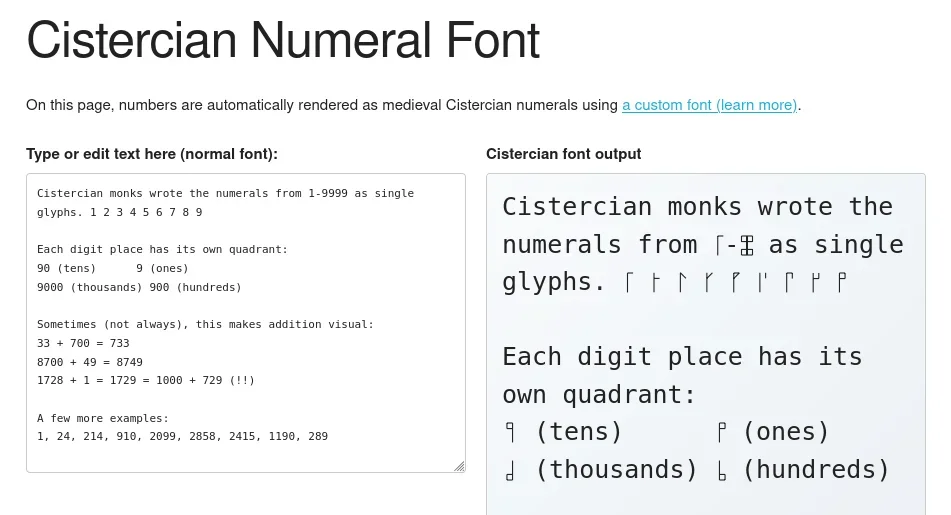
중세 시대 숫자, 커스텀 폰트로 부활!
커스텀 폰트(Custom Font)를 활용하여 중세 시대의 시스테르 시토 숫자 표기법을 구현하여 시각적 표현을 극대화함
덧셈 연산(Addition) 시 시각적 피드백을 제공하는 독특한 특징을 보이며, 필기 방식의 장점을 강조함
글리프(Glyph) 디자인의 혁신성과 유니코드(Unicode) 코드 포인트 할당에 대한 논의가 이루어짐
시스테르 시토 숫자 표기법의 시각적 특징
본 기술은 커스텀 폰트(Custom Font)를 활용하여 시스테르 시토 숫자 표기법을 구현, 덧셈 연산 시 시각적 피드백을 제공한다. 특히, 7-세그먼트 폰트(7-segment font)와 유사하게 숫자를 표현하여 직관성을 높였다. 이러한 시각적 표현은 수학적 개념(Mathematical Concept)을 시각화하는 데 기여하며, 사용자 경험을 향상시킨다.
필기 방식과 인쇄 방식의 차이점
커뮤니티에서는 필기 방식의 혁신성을 강조하며, 인쇄 방식의 한계를 지적한다. 필기(Handwriting)는 개별적인 글리프(Glyph) 생성이 자유롭고, 즉각적인 공유가 가능하다. 반면, 인쇄는 사전 정의된 글리프(Predefined Glyph)를 사용해야 하므로, 새로운 글리프 추가에 제약이 따른다. 이러한 차이는 글꼴 디자인(Font Design)의 혁신을 저해하는 요인으로 작용한다.
유니코드(Unicode) 코드 포인트 할당 및 효율성
논의에서는 시스테르 시토 숫자에 대한 유니코드(Unicode) 코드 포인트 할당 필요성이 제기되었다. 또한, 글리프(Glyph) 표현의 효율성에 대한 질문도 나왔다. 시스테르 시토 숫자는 글리프당 13비트 이상을 사용하며, 중국어(Chinese)와 같은 다른 표기법과의 비교를 통해 효율성을 평가할 수 있다. 이러한 논의는 글꼴 디자인(Font Design)의 기술적 측면을 심층적으로 탐구한다.